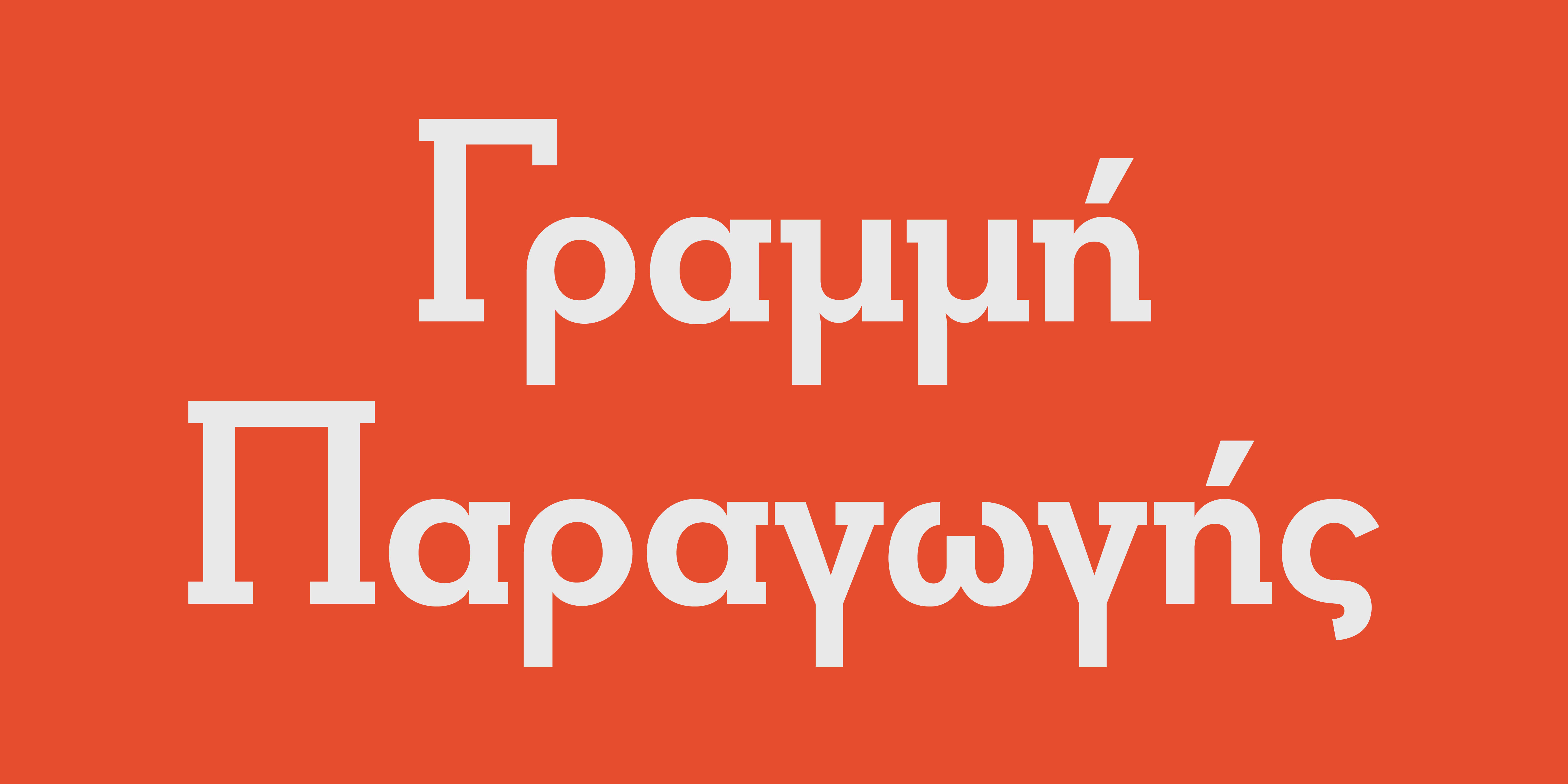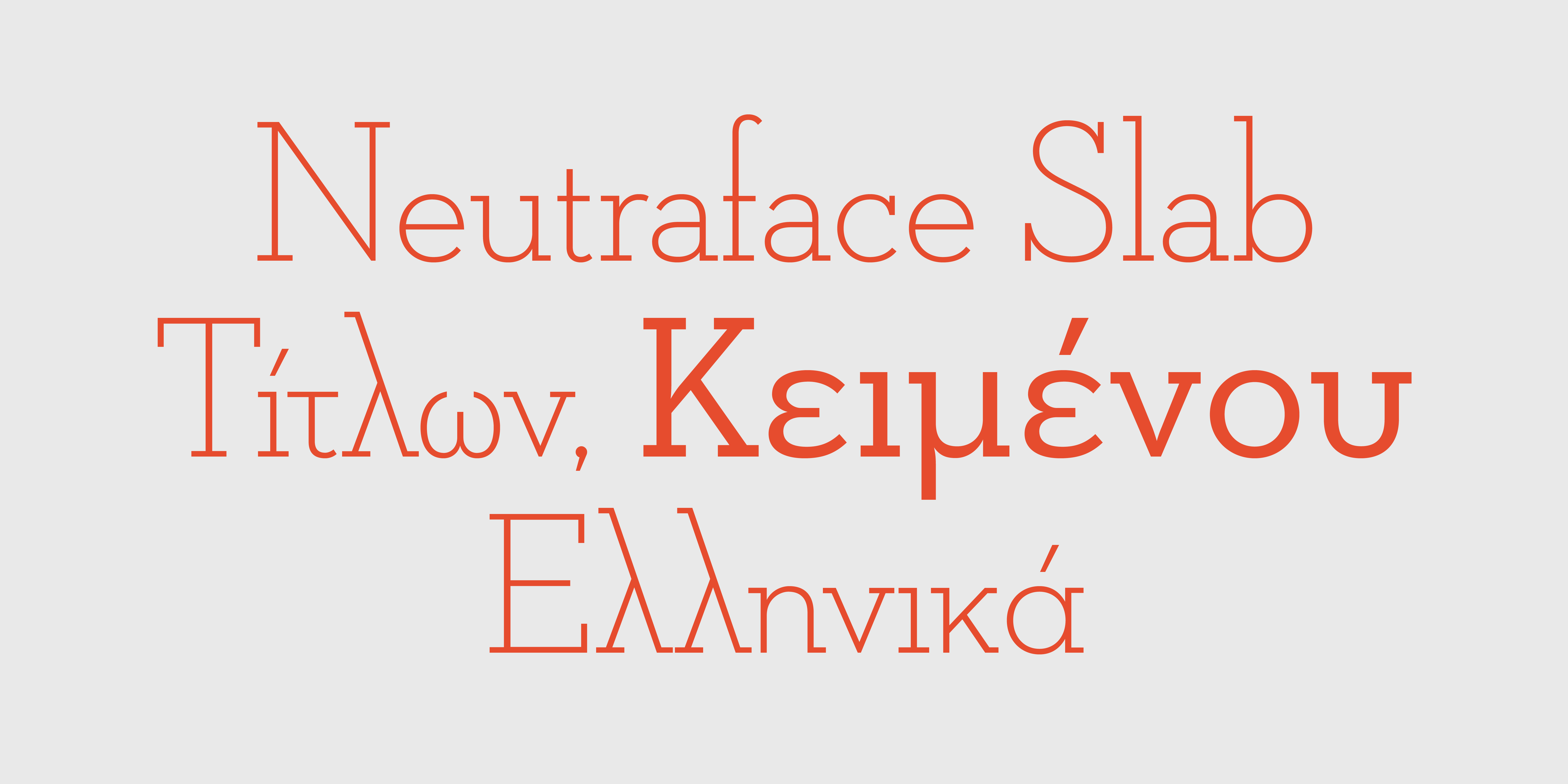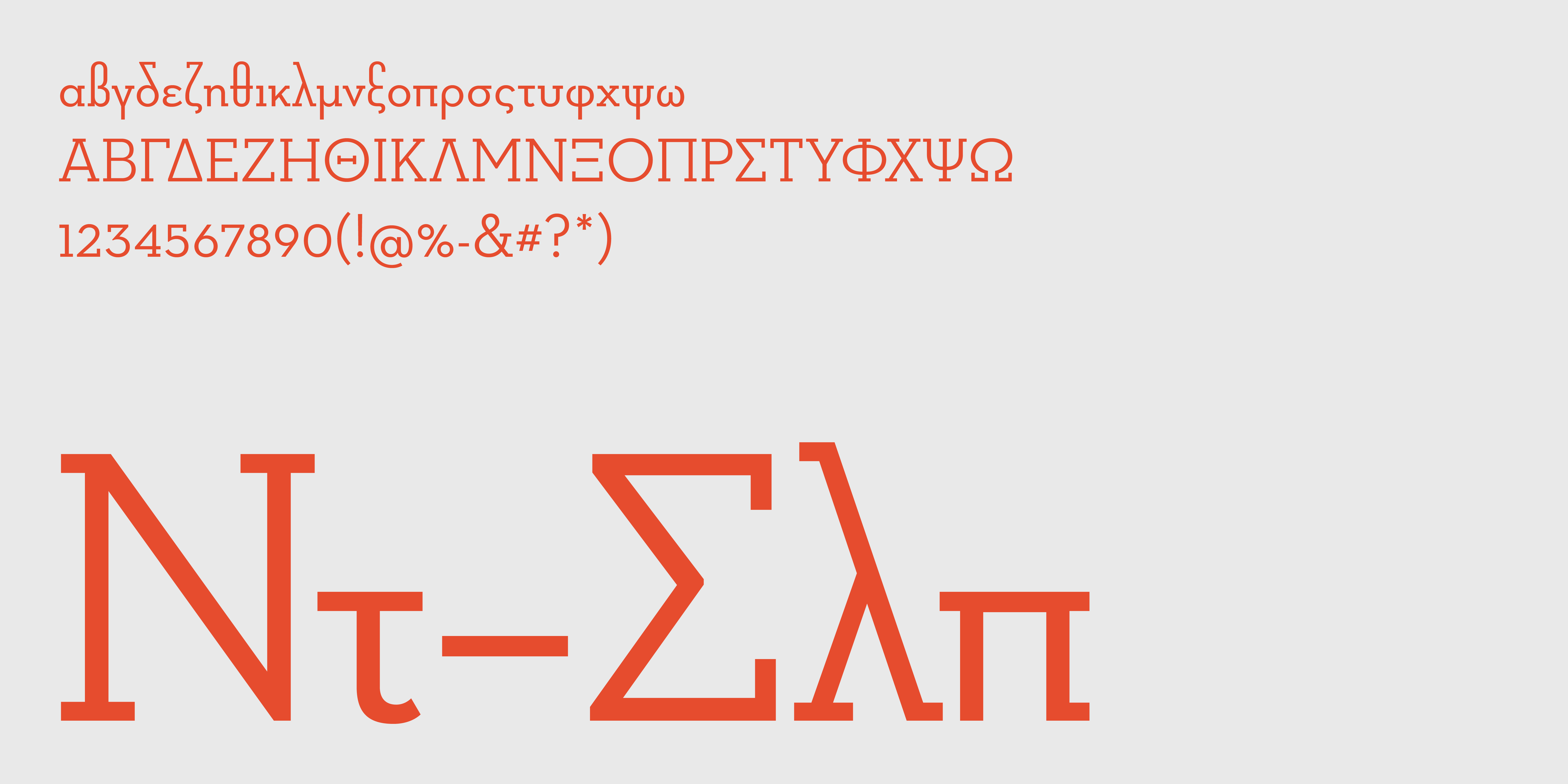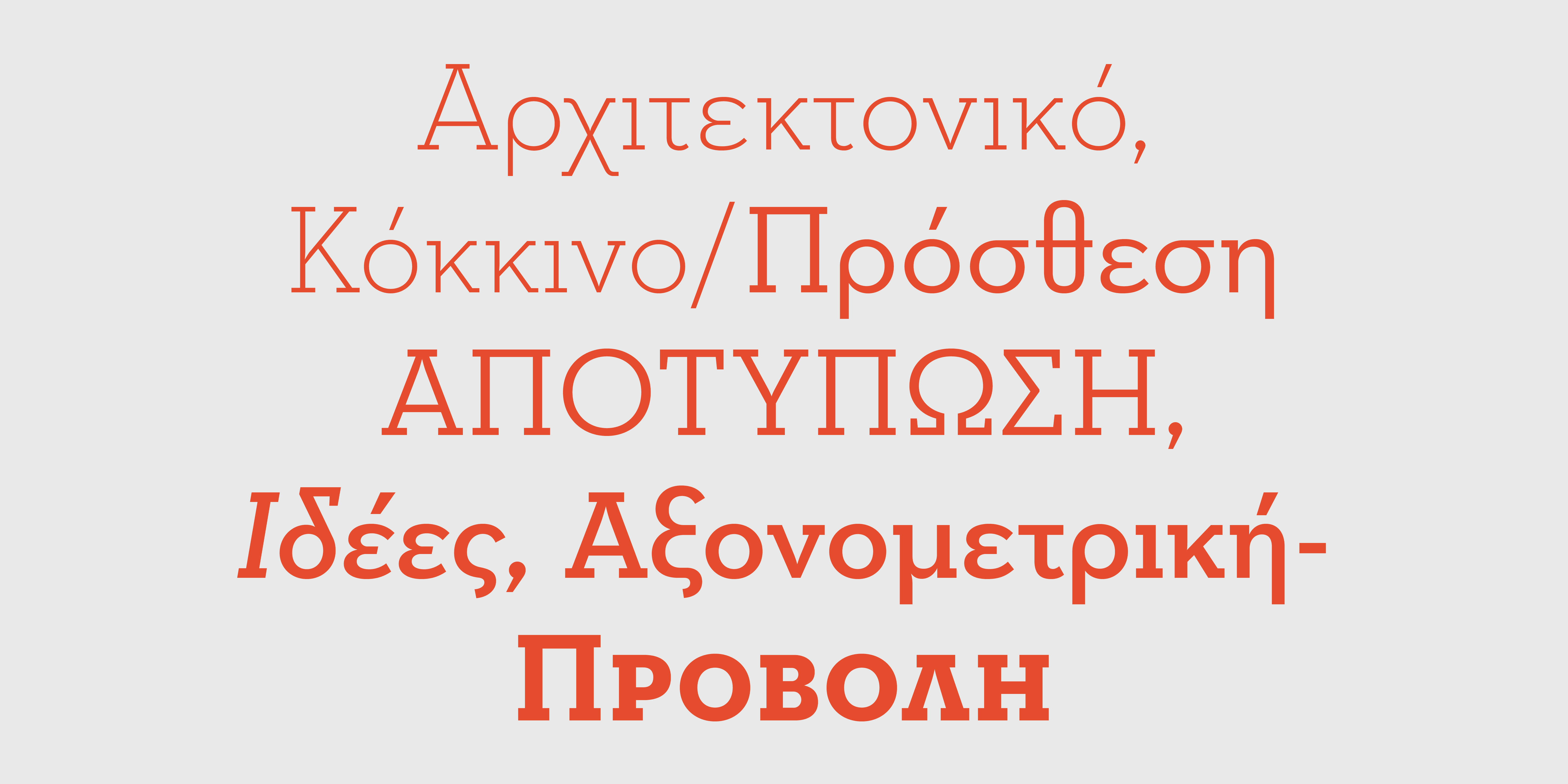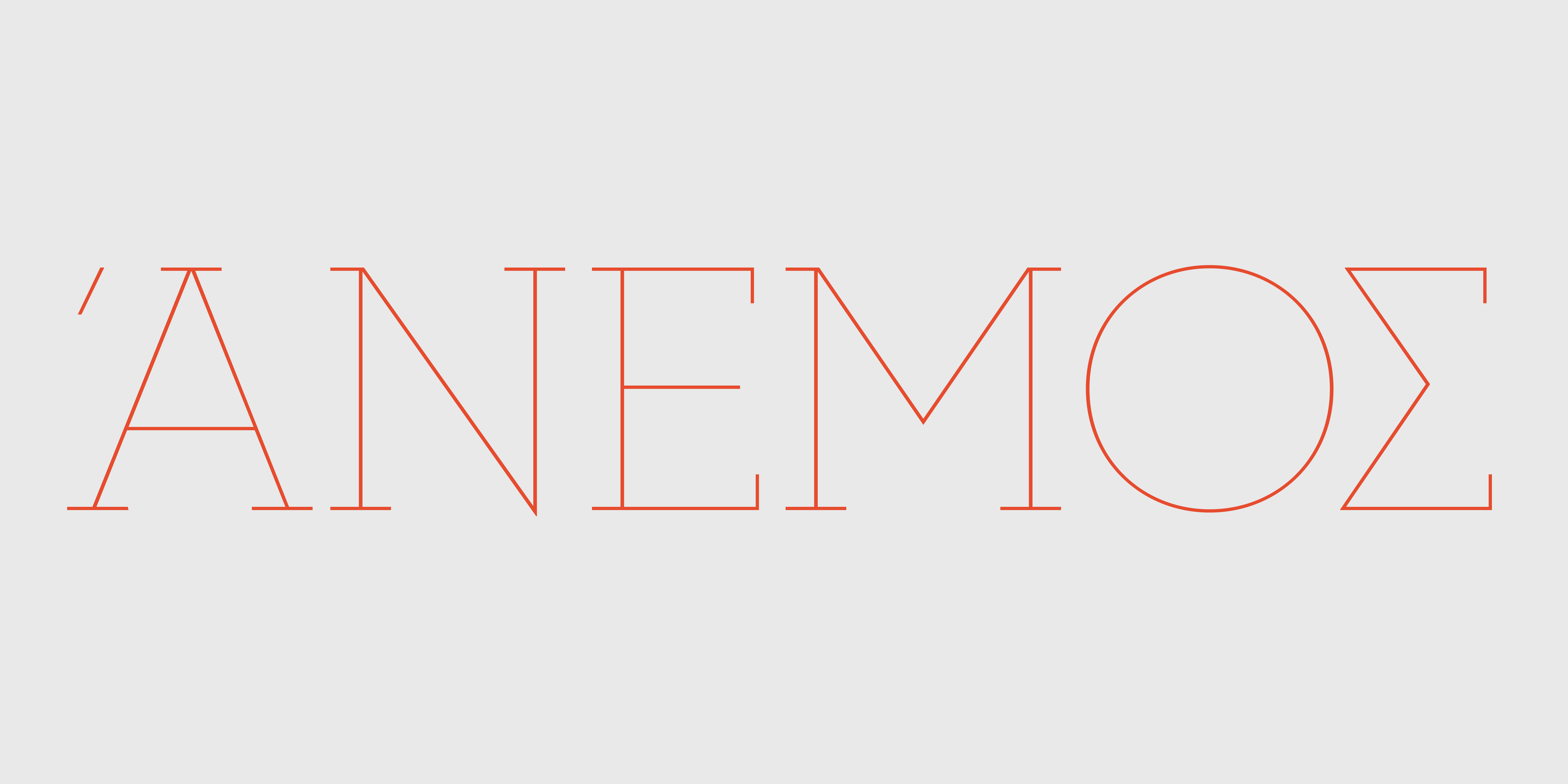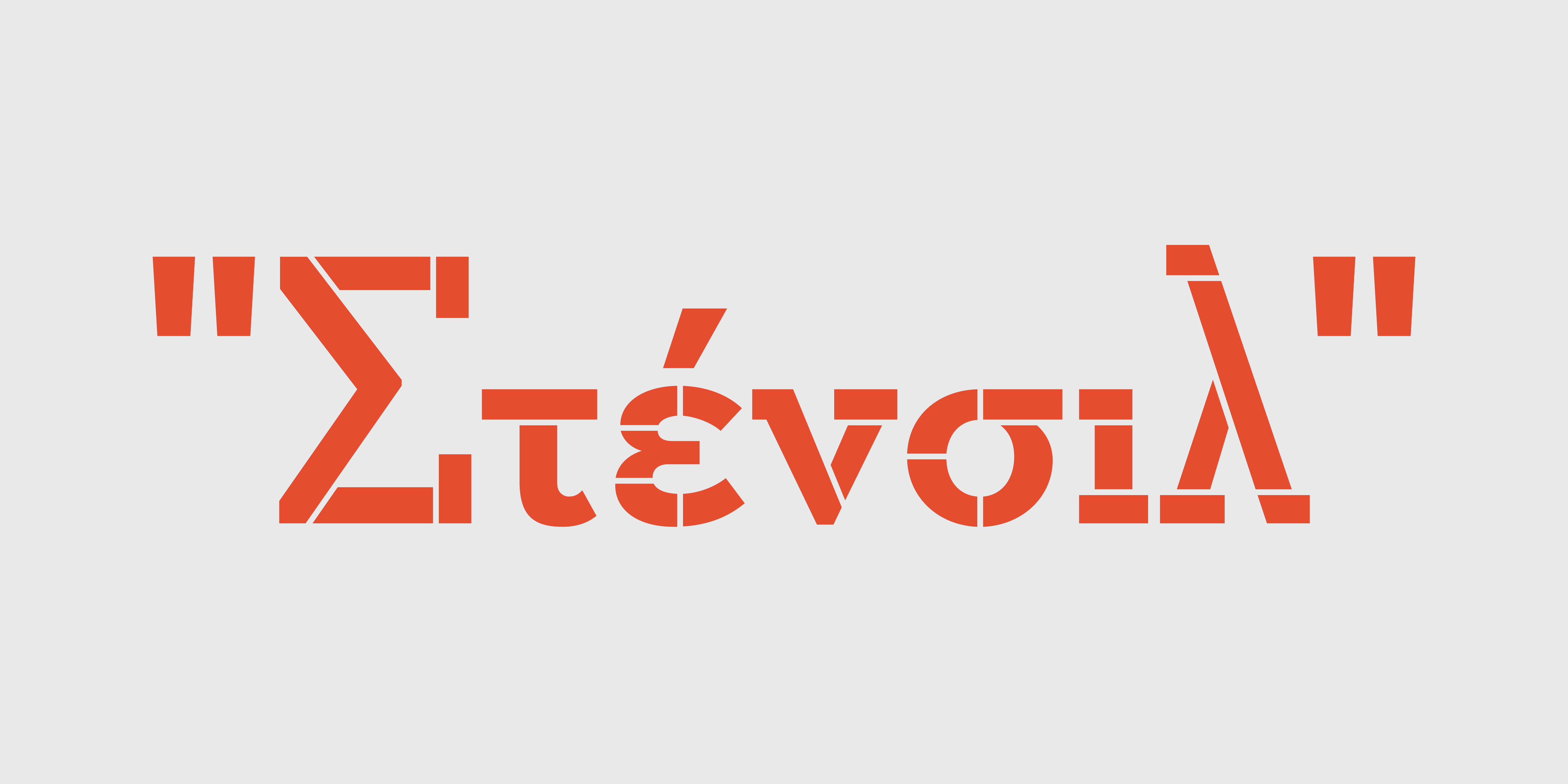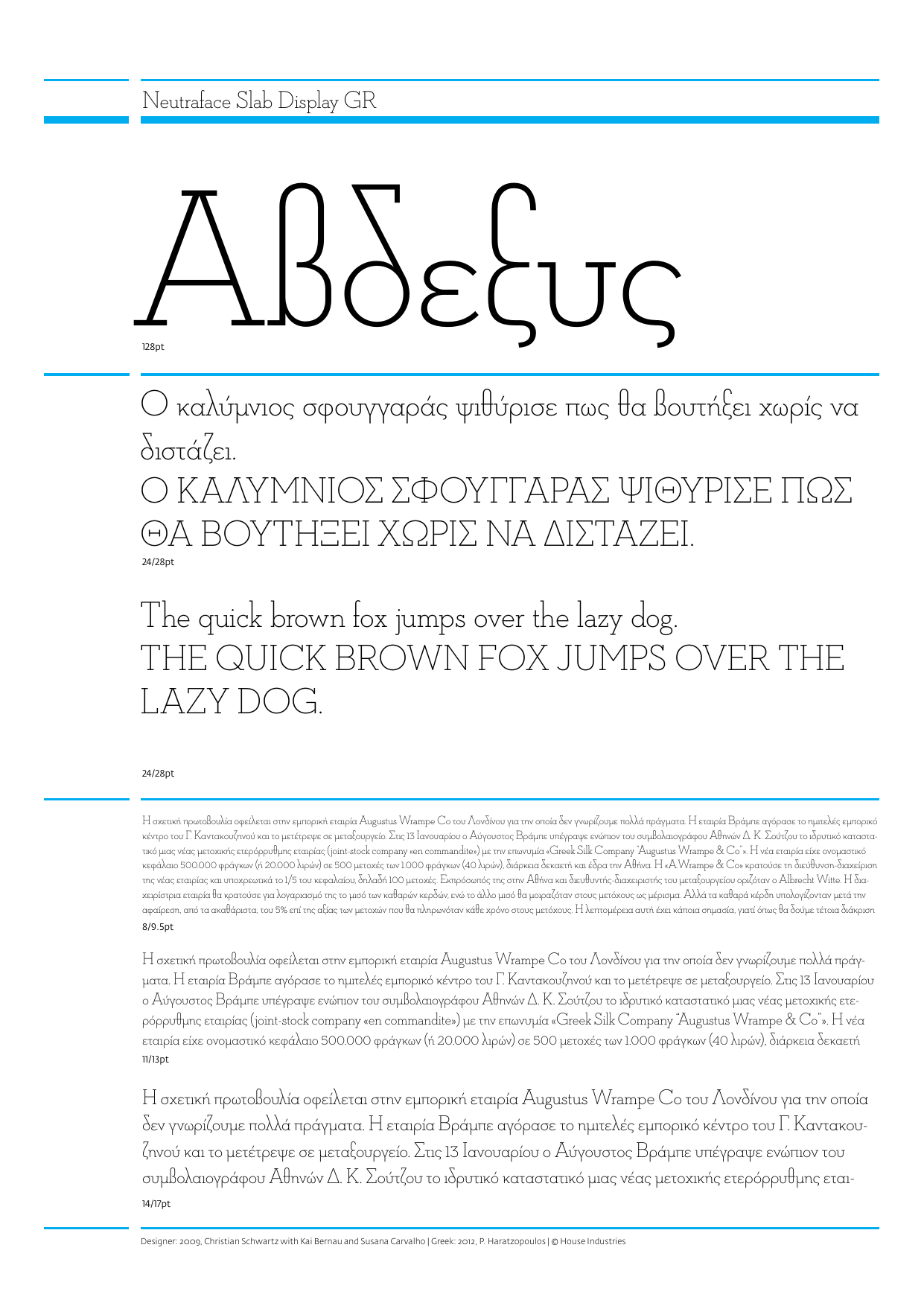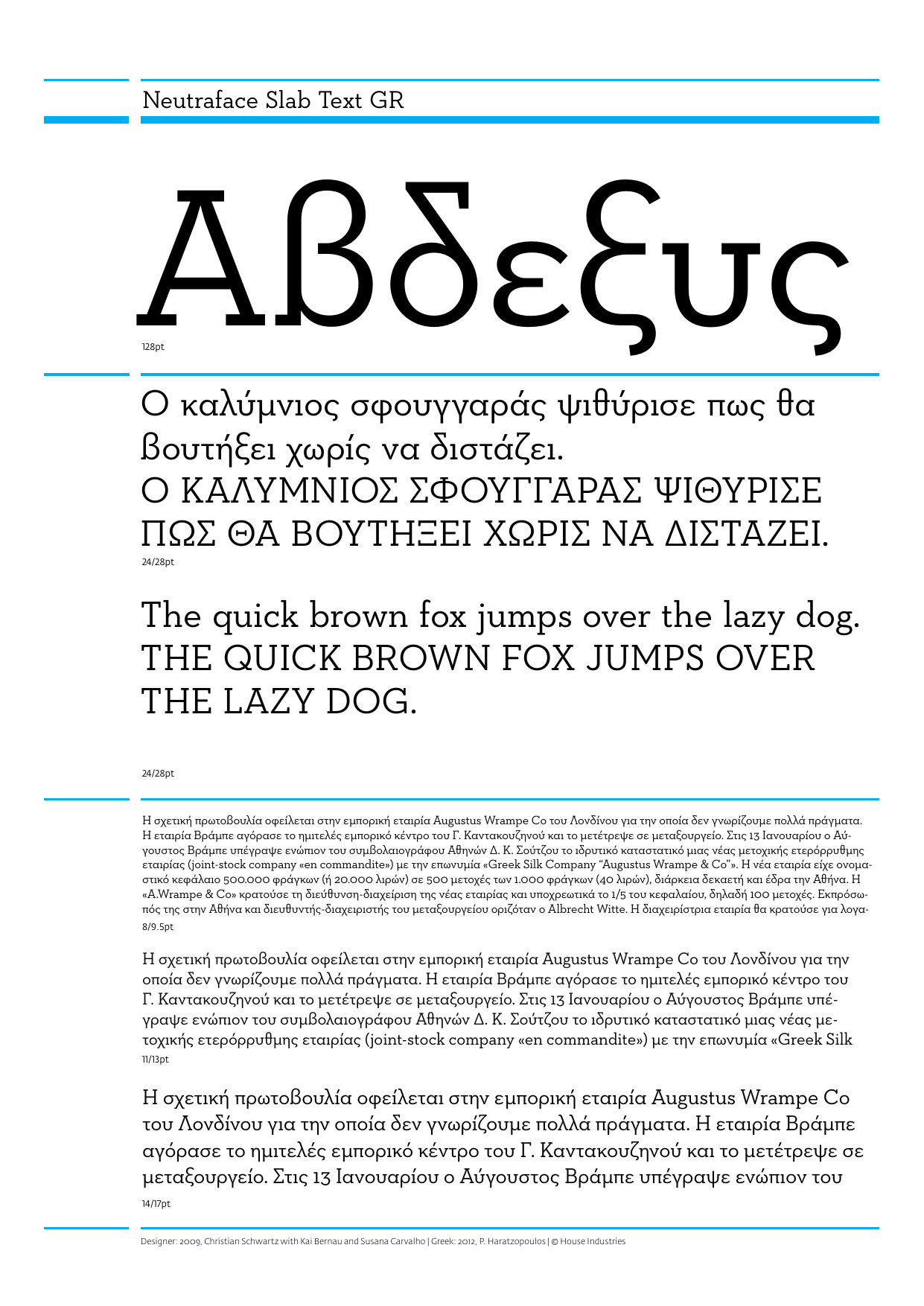
Neutraface Slab Ελληνικά
Η Neutraface Slab είναι επέκταση της δημοφιλούς Neutraface. Περιλαμβάνει δύο εκδοχές, για Κειμένο και Τίτλους σε Greek, με πλήθος εναλλακτικών χαρακτήρων, μικρά κεφαλαία, διαφορετικά είδη αρίθμησης και άλλα OpenType χαρακτηριστικά. © House Industries, Σχεδιαστής Christian Schwartz, Ελληνική έκδοση Παναγιώτης Χαρατζόπουλος